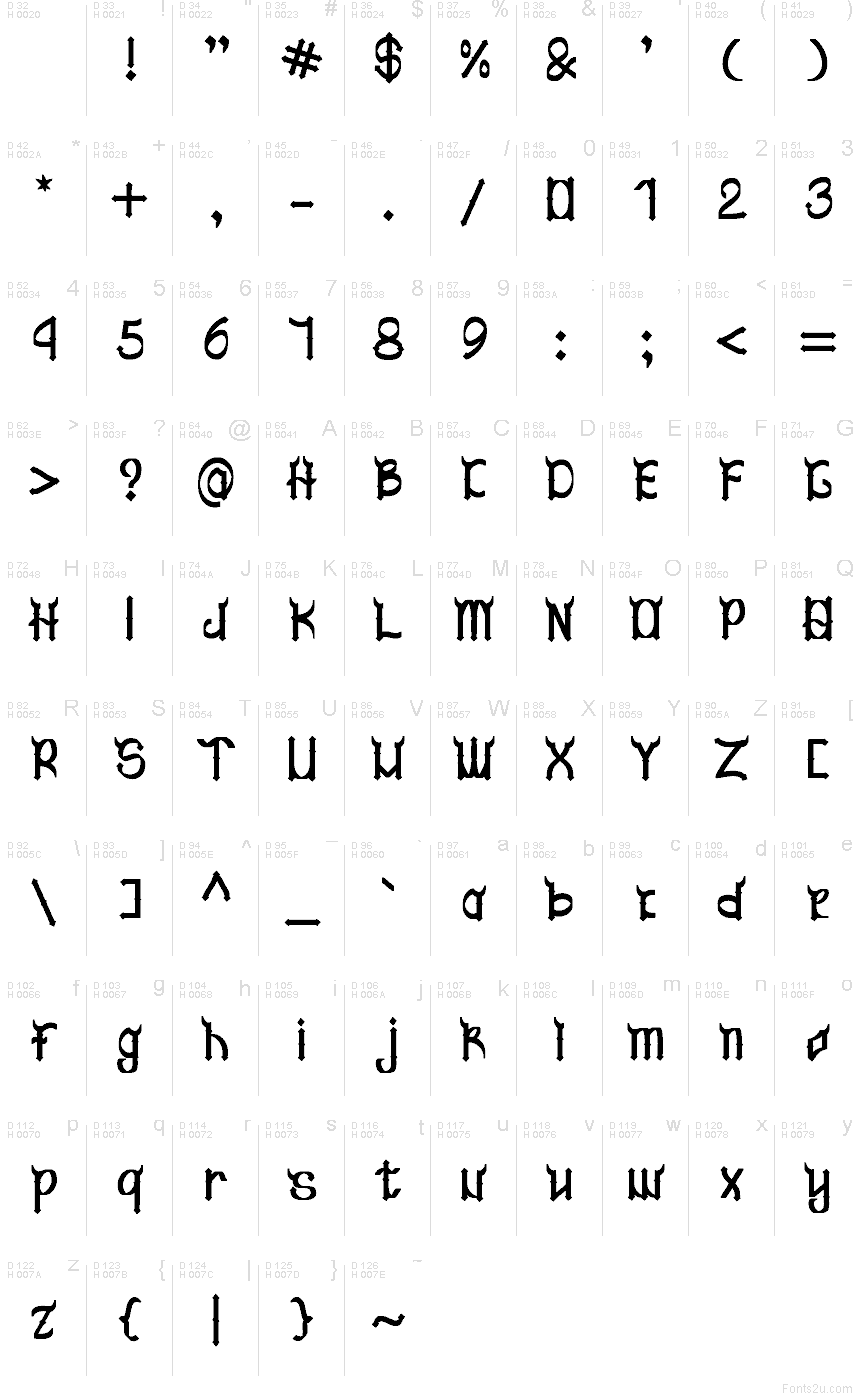
Metaliva od Yumnacreative je bezplatné moderní gotické písmo s tvrdou estetikou blackletteru. Písmena spojují vysokou vertikální hmotnost s ostrými hroty, rozštěpenými konci a drobnými rohovitými výstupky, které působí na první pohled středověce, ale jsou upraveny pro moderní titulkovou sazbu.
Hodí se pro hudební branding, titulky na plakátech, módní editorialy, obaly a úvodní kartičky, kde toto bezplatné písmo dodá temnou atmosféru bez přílišného zdobení. Využijte ho v krátkých nadpisech, logách nebo monogramových iniciálách, protože opakující se hroty a zářezy dodávají i pár písmenům silný, ceremoniální výraz.
Metaliva